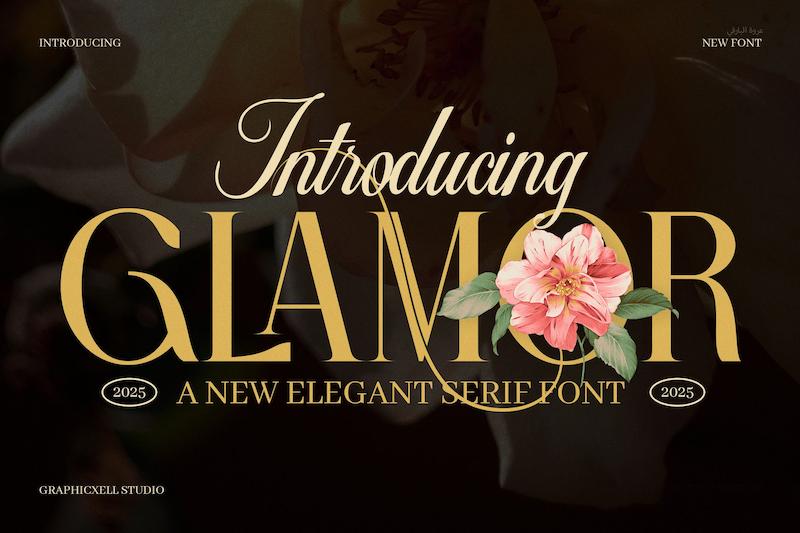
فونت دیسپلی گلامور یک تایپفیس سریف با طراحی زیبا است که تعادل کاملی بین جذابیت کلاسیک و سبک امروزی برقرار میکند. علاوه بر این، خطوط با کنتراست بالا، سریفهای تیز و منحنیهای نرم آن، حسی لوکس و شیک به طراحیهای شما میبخشند. به همین دلیل، این فونت برای پروژههایی که میخواهند حس ظرافت را منتقل کنند و در عین حال یک لبهٔ معاصر داشته باشند، ایدهآل است.
چه در حال طراحی لوگو، تیتر مجله، کارت دعوت عروسی یا بستهبندی باشید، فونت گلامور حس کمال و آراستگی را اضافه میکند. در واقع، فرمهای حروف جسورانه و در عین حال ظریف آن به وضوح برجسته میشوند و آن را به یک انتخاب برتر برای برندسازی لوکس و همچنین استفاده در انتشارات سطح بالا تبدیل میکنند. علاوه بر این، این فونت وزنها و حالتهای ایتالیک متعددی را ارائه میدهد که به شما امکان میدهد سلسلهمراتب تایپوگرافی بصری غنی ایجاد کنید.
خطوط با کنتراست بالا برای تأثیرگذاری چشمگیر
حروف ایتالیک و آلترنیت الگانت
لیگچرهای شیک که جذابیت میبخشند
پشتیبانی چندزبانه برای پروژههای جهانی
وزنهای متعدد: رگولار، مدیوم و بولد
جزئیات تمیز و تیز برای وضوح در اندازههای بزرگتر
به دلیل این ویژگیها، گلامور ابزاری انعطافپذیر برای بسیاری از زمینههای خلاقانه، از مد و فشن گرفته تا برندسازی بوتیک هتلها است.
این فونت در کاربردهای مختلفی میدرخشد، مانند:
کاور مجلات مد و مقالات تحریریه
کارت دعوت عروسی و برندسازی رویدادها
لوگوهای بوتیک و طراحی وب ظریف
عناوین یا تیترهایی که نیاز به جلب توجه دارند
علاوه بر این، بهخوبی با فونتهای سادهٔ سنس سریف جفت میشود، یا میتوانید آن را بهتنهایی برای ایجاد یک تأکید قوی استفاده کنید.
اگر به دنبال فونتی هستید که جذابیت (گلامور)، سبک و خوانایی را در کنار هم بیاورد، این یک انتخاب عالی است. در واقع، این فونت طراحی شده است تا پروژههای شما را صیقلی و شیک نشان دهد و در عین حال خواند آسان باقی بماند. فونت دیسپلی گلامور چیزی فراتر از یک تایپفیس است—این راهی است برای بخشیدن یک هویت منحصربهفرد و سطح بالا به کار شما.
طبقهبندی: سریف